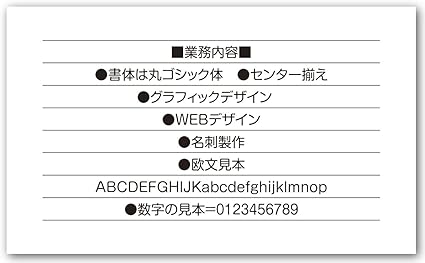
ゴシック系 まずはゴシック体から。頻繁に使う機会があることや、他の自体に比べて作りやすいこともあり、かなりの数があり充実しています。 マキナス マキナス 4 シリーズをダウンロード 刻ゴシック 刻ゴシックフォントをダウンロード 廻想体ネクストb.
名刺 フォント おすすめ ゴシック. 名刺を作りたい時や、 自分のイメージ通りのバナーを制作したい時、フォントの雰囲気が合わなくて名刺やバナーの仕上がりが微妙になってしまうことってありますよね。 webデザイン に大きな影響を与えるフォント。 無料でも 商用利用可能の フォントがたくさんあることはご存知ですか?. 名刺用紙の選び方が知りたい。 名刺用紙にはどんな種類があるのか知りたい。 おすすめの名刺用紙を教えて欲しい。 名刺用紙には紙の厚さや材質など、さまざまな種類があります。 初めて自作名刺に. フォントサイズは最低でも7pt以上で 65pt以下になると、視認性が下がります。連絡先や事業内容はフォントサイズを小さくしがちですが、見やすさを考えて7pt以上にしましょう。 名前のフォントは18〜19ptが最適 名前は名刺の中で最重要な情報です。.
ゴシック系 まずはゴシック体から。頻繁に使う機会があることや、他の自体に比べて作りやすいこともあり、かなりの数があり充実しています。 マキナス マキナス 4 シリーズをダウンロード 刻ゴシック 刻ゴシックフォントをダウンロード 廻想体ネクストb. Google Fontsのサービスなど、最近では無料で使えるフォントも増えてきました。 しかし、数もかなり多くどんなフォントを使えばいいのか迷ってしまいますよね。 今回はWebデザインの現場からよく使う定番のフォントをご紹介いたします。 よく使う日本語フォント ゴシック体. ゴシック系のフォントで、 Windowsに標準搭載 されています。 とても読みやすいので、ビジネス文書や名刺に使う方が増えているフォントです。 ⇒メイリオのテンプレートをダウンロード ゴシック体のおすすめフリーフォント.
本日は、宛名印刷の書体について考えて見たいと思います。 私的な感覚の話も有り、人によって異なる意見もあるかもしれませんが、参考にしてください。 目次お勧めの書体 C&G流麗行書体ミミズのはったような書体C&G流麗行書体誰からも好かれる楷書体太い楷書体は人気無し行書体. 名刺を作っているのですが、 フォントはms p 明朝を使おうと思っています。 これは一般的なんでしょうか。 他に、普通名刺ではこういうフォントを使うよ というのがあれば教えてください。 またローマ字や数字などは. Google Fontsのサービスなど、最近では無料で使えるフォントも増えてきました。 しかし、数もかなり多くどんなフォントを使えばいいのか迷ってしまいますよね。 今回はWebデザインの現場からよく使う定番のフォントをご紹介いたします。 よく使う日本語フォント ゴシック体.
おすすめフォント2「秀英丸ゴシック」 つづいて二つ目は 「秀英丸ゴシック」 です。 秀英体は、大日本印刷サマが、その前身である秀英舎の活字書体を引継ぎ、開発を行ってきた伝統あるフォントです。. MSゴシックと同様のゴシック体ですが、MSに比べて文字間隔が広く取られていて、プレゼンのスライドに使用するのに向いています。 Windows 81 & Windows 10 Windows 81から搭載されたフォントとして「游ゴシック」があります。. 名刺を作っているのですが、 フォントはms p 明朝を使おうと思っています。 これは一般的なんでしょうか。 他に、普通名刺ではこういうフォントを使うよ というのがあれば教えてください。 またローマ字や数字などは.
ゴシック体は、 縦と横の線の太さがほぼ均一で、起筆点・終筆点が角張っている という特徴があります。 こちらもよく使われるフォントの一つです。コンピューターで標準的に使用されていて、ディスプレイの解像度の都合にも適しています。.